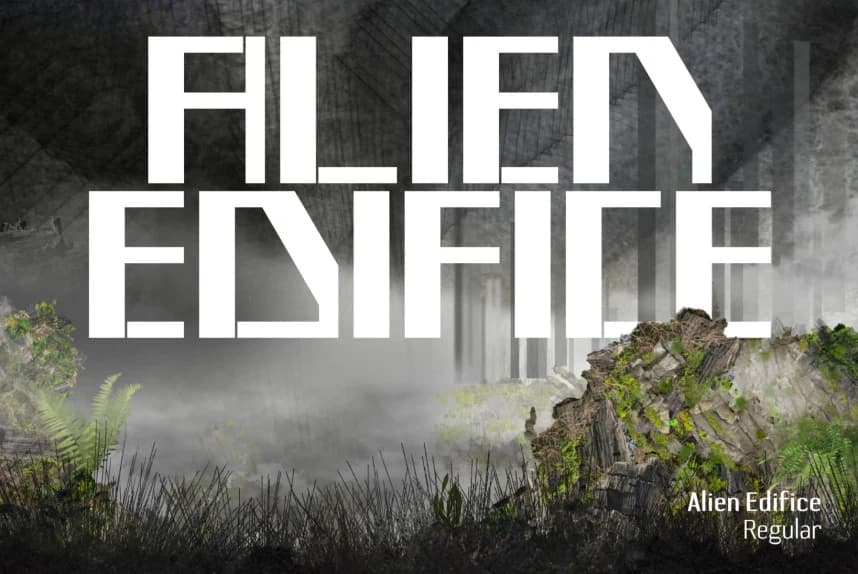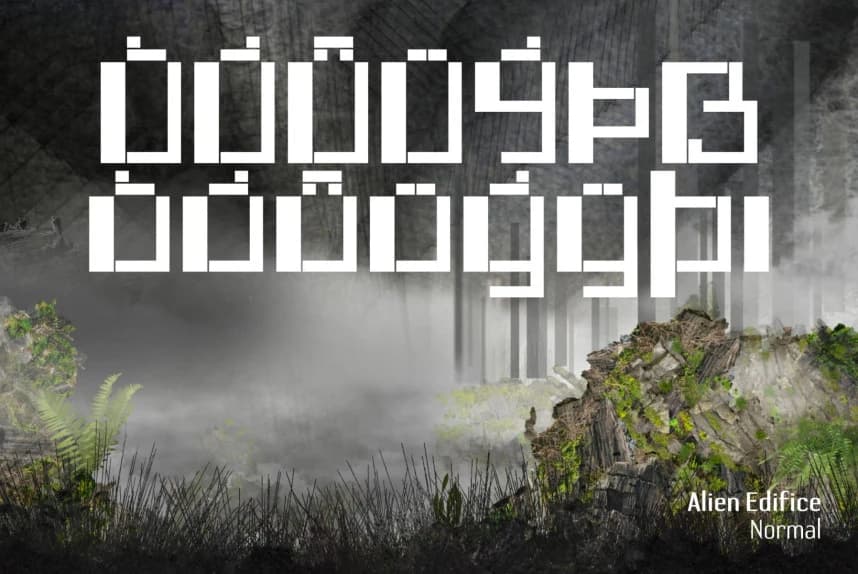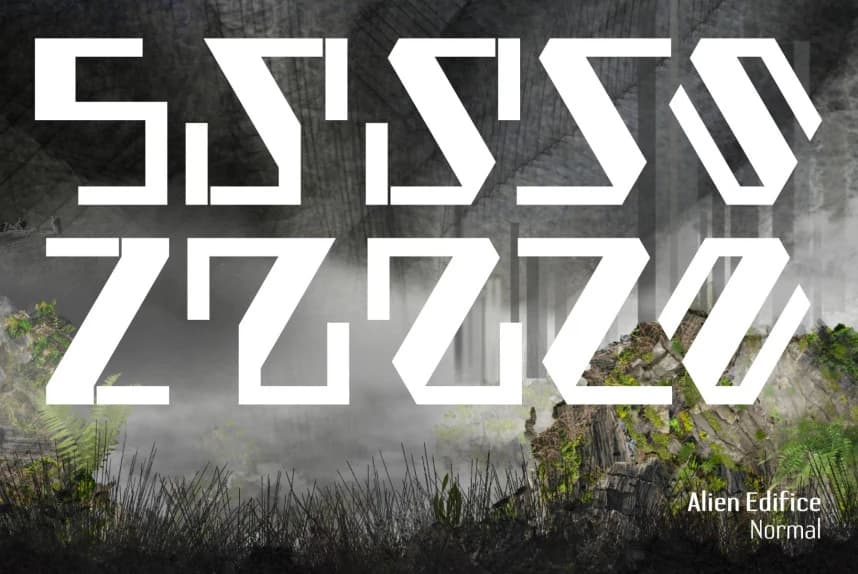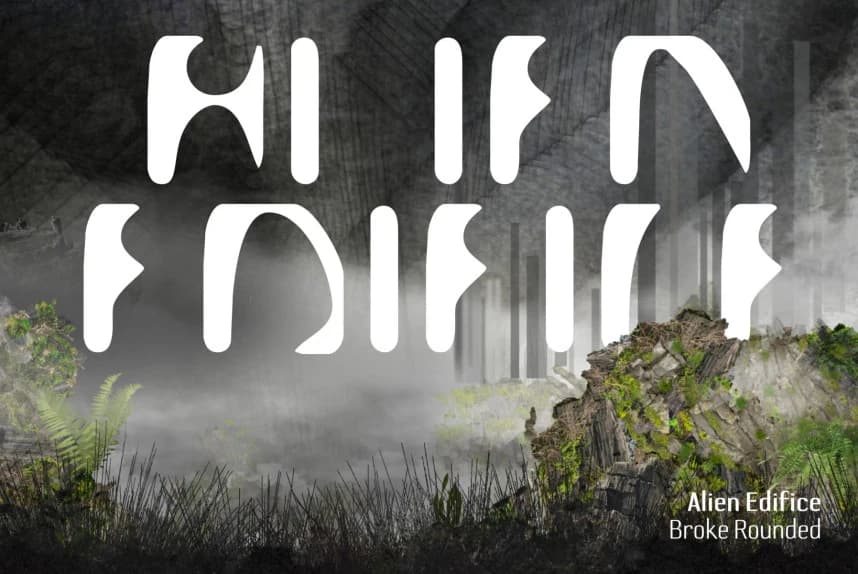
Alien Edifice Font Family
Alien Edifice Font Family, FontLab Studio 5'te yaklaşık 10 yıl önce tasarladığım brutalist bir başlık fontudur. Kısmen, 1968 yapımı Stanley Kubrick filmi ‘2001: A Space Odyssey’nin başında görünen siyah monolitten esinlenmiştir. Bunu hiç yayımlamadım çünkü kimsenin ilgileneceğini düşünmüyordum.
Alien Edifice Font Family, brütalist bir başlık yazı tipidir; on yıldan uzun bir süre önce FontLab Studio 5'te tasarladım. Kısmen, 1968 yapımı Stanley Kubrick filmi '2001: Bir Uzay Macerası'nın başında görünen siyah monolitten ilham almıştır. Böyle keskin, geometrik bir yazı tipine ilgi gösterecek kimseyi düşünmediğim için hiçbir zaman yayımlamadım.